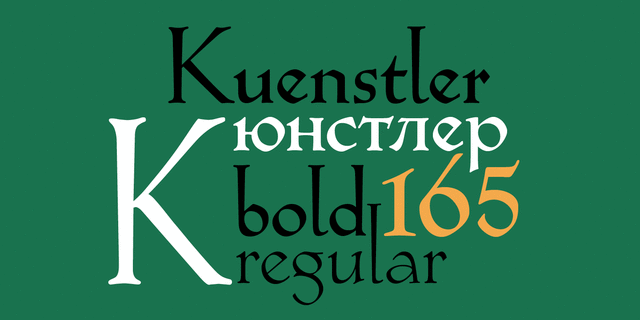
Шрифт фирмы Bitstream на основе рисунка гарнитуры Кох-Антиква немецкого каллиграфа Рудольфа Коха (Klingspor, 1922). Этот изящный шрифт, также известный как Локарно и Ева – самая известная работа одного из величайших мастеров шрифта ХХ века. Кох-Антиква – тонкий акцидентный шрифт с мелким очком строчных знаков и высокими верхними выносными элементами, грациозно сужающимися книзу. Кох-Антиква был чрезвычайно популярен в рекламе в период между двумя мировыми войнами. Его нужно применять умеренно для создания ощущения «ретро» в рекламной, книжной и другой печатной продукции. Кириллическая версия в двух начертаниях, включающая альтернативные варианты строчных, разработана Изабеллой Чаевой. Выпущена в 2008 году компанией ПараТайп.